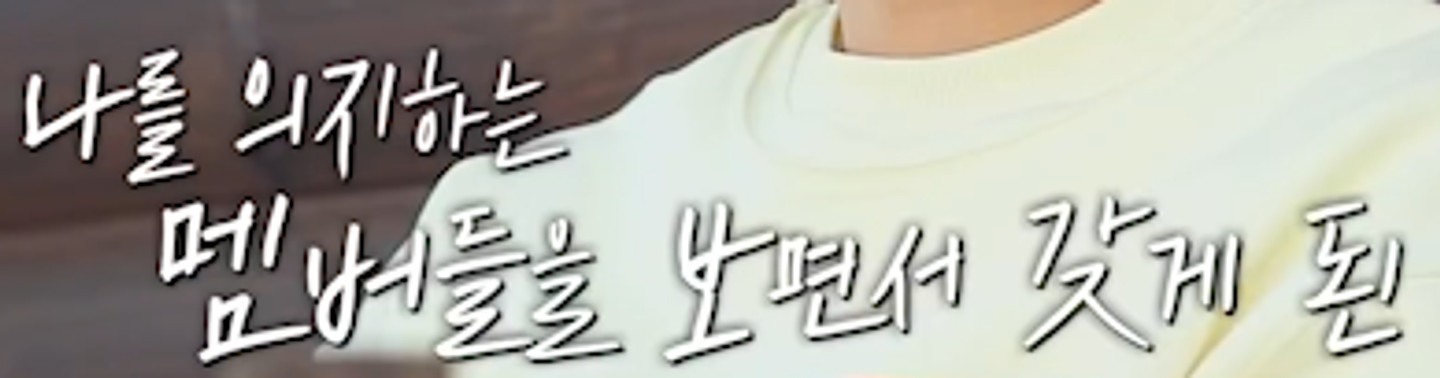
사진에 있는 이 서체의 이름은 Nanum Square인가요? 아니면 Nanum Square Round인가요? 아니면 Nanum Octagon(2022년 10월-2023년 예정)인가요? (참고로 Nanum Octagon은 Nanum Square, Nanum Square Round의 중간지점 영문 기반 제목용 서체로 2022-2023년 공개 예정)